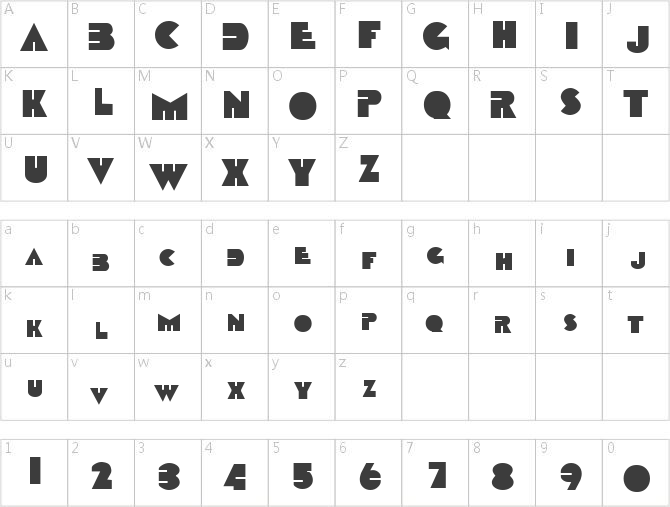
字體名稱: Circula
Circular-FC
Circular-FC介紹
Circular-FC字體字庫是一款讓人賞心悅目、百看不厭的英文字體,適合各類廣告和產(chǎn)品包裝設(shè)計應(yīng)用,字體大小0.01MB,格式為ttf字體,上傳用戶是昊天金誠,作者/版權(quán)方為未知